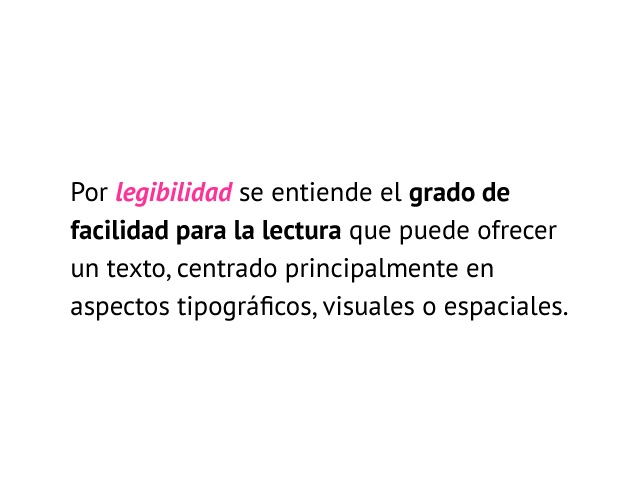
Por legibilidad se entiende el grado de facilidad para la lectura que puede ofrecer un texto, centrado principalmente en aspectos tipográficos, visuales o espaciales.
En el caso del diseño editorial, la buena legibilidad se logra con el buen empleo y selección de la familia tipográfica. El buen calibre de nociones como interletrado, interpalabra y el grisado de texto ayudan a la buena legibilidad de aquello que se intenta comunicar.